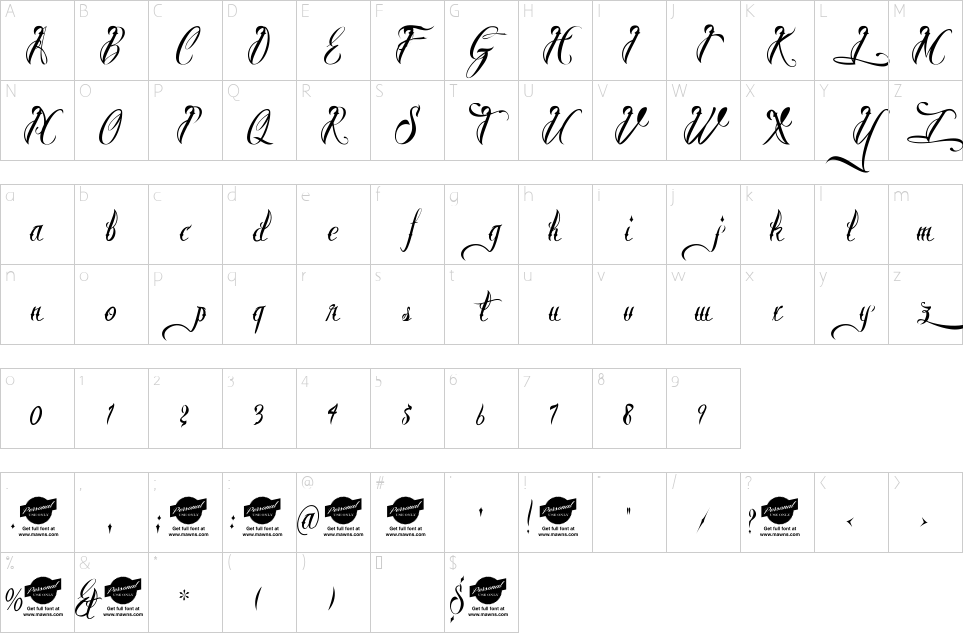
A fonte Brother Tattoo é uma opção única e criativa para quem busca uma identidade única em suas obras de arte corporais. Desenvolvida pelo designer desconhecido Måns Grebäck, essa fonte tem sido popular entre os fãs de tattoos e artistas gráficos que buscam um estilo único. Com um design arredondado e moderno, a Brother Tattoo permite criar texturas interessantes e uma textura de tatuagem semelhante. Com um baixo número de downloads, é um raro tesouro para a sua biblioteca de fontes. Estamos ansiosos para que você descubra o fascínio desta fonte única e adicione seu próprio toque único à sua arte corporal. Descubra mais sobre a fonte Brother Tattoo e participe desta descoberta incrível.